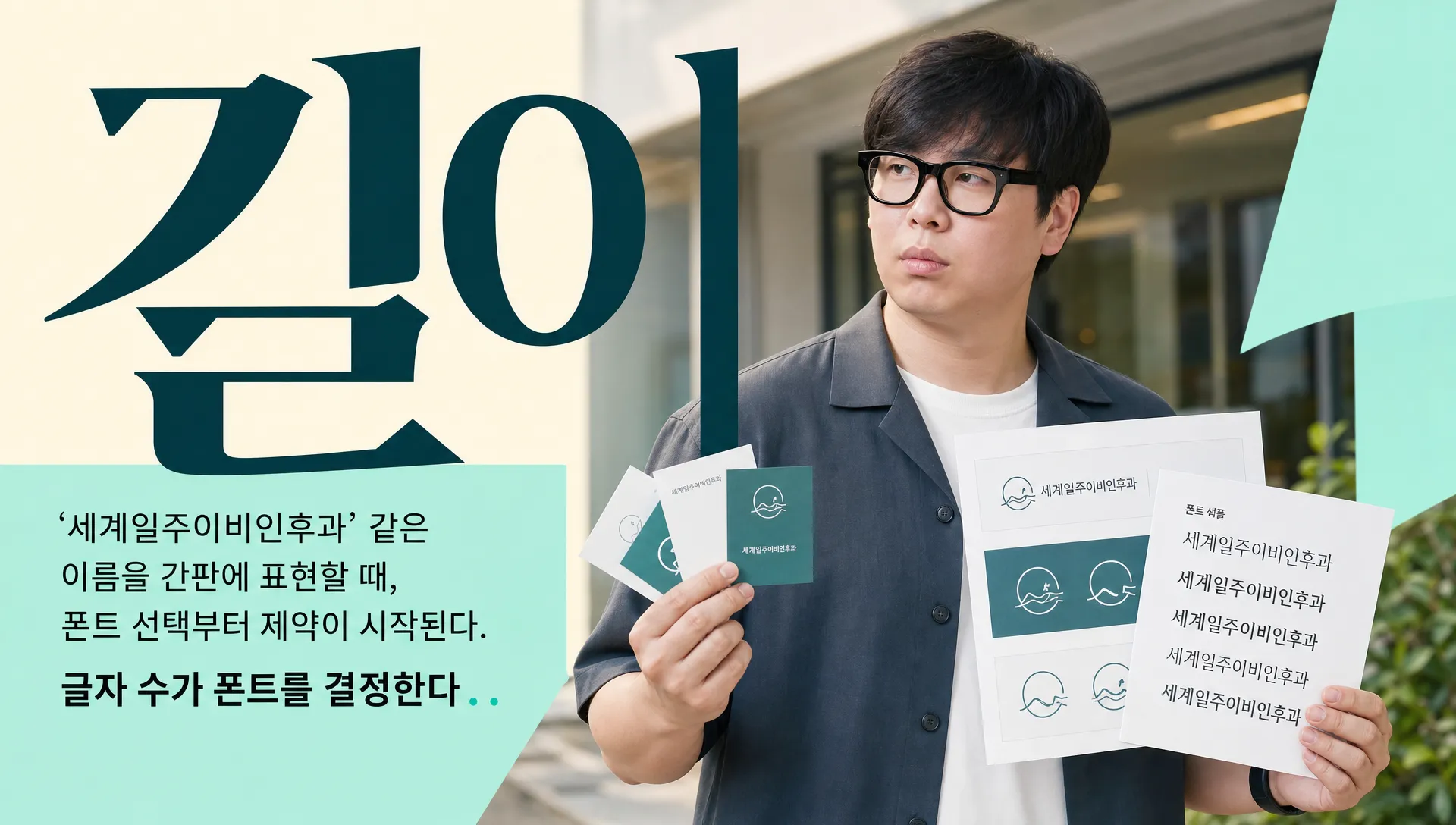
간판에서 이름이 길수록 폰트가 흐릿해진다 — 글자 수가 결정하는 폰트 선택
치과명 글자 수·구성에 따라 폰트 선택이 달라진다. 간판·명함·앱에서도 또렷하게 읽히려면 어떤 폰트를 골라야 할까.
“세계일주이비인후과” 같은 이름을 간판에서 똑같이 표현하려다 보면, 폰트를 선택하는 순간부터 제약이 시작된다.
폰트는 단순히 ‘어떤 글꼴을 고를까’의 문제가 아니다. 이름에 들어간 글자 수 하나가 폰트의 ‘굵기·간격·너비’ 전체를 결정 지은다. 5글자 이하의 짧은 이름은 굵고 특성 있는 폰트도 견딜 수 있지만, “○○○○○○○치과의원” 같은 긴 이름은 얘기가 달라진다.
긴 치과명일수록 폰트 선택이 좁혀지는 이유
간판에서 치과명이 읽혀야 하는 가장 기본 거리는 3~5미터다. 이 거리에서 글자 하나하나를 구분하려면 적절한 ‘무게’가 필요하다. 하지만 글자가 7자 이상으로 늘어나면, 같은 폰트 크기 안에 더 많은 글자를 집어넣어야 한다. 이때 개성 있는 세리프 폰트나 지나치게 얇은 웨이트(Light, Thin)는 작은 크기에서 글자 획이 흐려진다.
실제로 치과 간판 디자인 현장에서 본다면, 짧은 이름은 굵기 있는 폰트(Bold, Extra Bold)도 시도할 여지가 있지만, 긴 이름은 ‘안정적으로 읽히는 Regular 굵기·고딕 계열’로 거의 고정된다. 왜냐하면 그래야 8글자 이상의 이름도 3미터 거리에서 각 글자가 뭉개지지 않기 때문이다. 원장명과 지역명, 과목명까지 담다 보니, 시각적으로는 한계가 생기는 셈이다.
작은 명함·앱에서도 선명하려면 글자 간격이 결정한다
간판은 한 사람이 선 거리에서 본다면, 명함은 손 안의 10센티 거리에서 본다. 간판에서는 괜찮았던 폰트도 명함 크기로 축소되면 급격히 흐려진다. 특히 글자가 많으면 자간(글자 사이 간격)이 좁아져서, 작은 크기에서는 글자들이 붙어 보인다.
이때 해결법은 포인트 크기를 크게 하는 것보다, 오히려 자간을 넓혀주는 것이다. 한글 폰트에서 자간을 +5~10% 정도 늘리면, 같은 크기의 폰트도 훨씬 또렷하게 보인다. 더 나아가 장평(글자의 가로 너비)을 90~95% 정도로 살짝 압축하면, 글자 수는 많지만 너무 옆으로 펼쳐지지 않으면서도 각 글자는 선명해진다.
스마트폰 앱의 프로필 이름 창이나 검색 결과에서 치과명이 표시될 때도 마찬가지다. 디스플레이 픽셀 크기가 정해져 있으므로, 폰트의 고딕 계열(노토 산스, 나눔 고딕)은 필수고, 자간을 약간 여유 있게 가져가면 모바일 화면에서도 한 글자씩 명확해진다.
굵기를 포기하지 말되, 고딕의 균형을 믿어라
글자가 많으면 Bold를 포기하고 Regular로 가야 한다는 일반적 조언이 있다. 하지만 실제로는 Regular 굵기의 고딕도, 자간만 잘 맞으면 충분히 강한 인상을 남긴다. 이미 숟가락-이미지(로고 심볼)가 있다면, 글자는 명확한 가독성과 일관된 무게감으로 브랜드를 지탱하는 역할을 하면 된다.
폰트 선택할 때 체크리스트: (1) 고딕 계열인가? (2) 어떤 매체에서든 균등한 무게감인가? (3) 자간을 조절할 여지가 있는가? 이 세 가지를 모두 만족하면, 7글자든 10글자든 어디에 놓여도 버티는 로고가 나온다.
이름이 결정되었다면, 그 이름에 맞는 폰트를 찾기보다는 그 폰트를 이름에 맞게 조정하는 작업부터 시작하자.